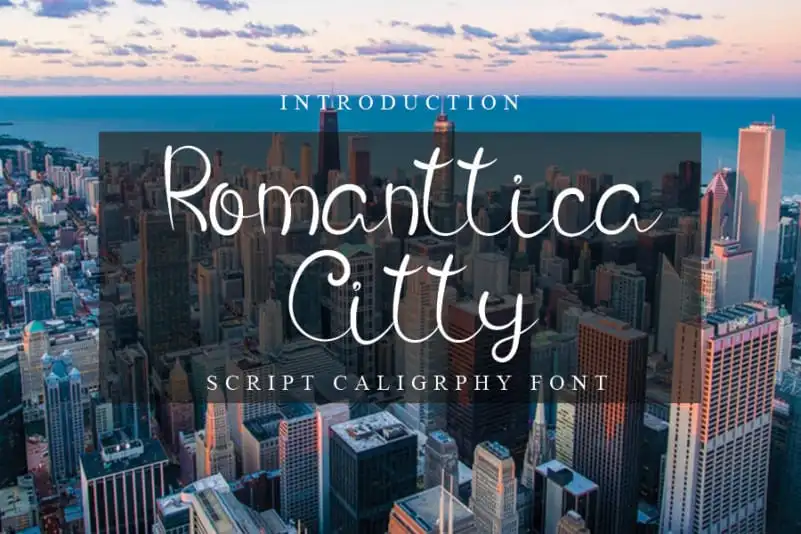
A “Romanttica Citty Script Font” é uma elegante escolha para designers apaixonados por letra escrita a mão. Esta fonte não apenas preserva os influentes traços do calligrafia clássica, mas também transmite um toque moderno e inovador. Com sua grande versatilidade, ela atende perfeitamente uma ampla variedade de ideias criativas – desde o design de cartões e títulos até a produção de materiais para escritório. Obrigado à equipe do inermediaSTUDIO por criar essa fonte única. A “Romanttica Citty Script Font” oferece aos designers um elemento visual que combina sofisticação com uma sensação atual, tornando-a uma opção perfeita para diferentes projetos de design.